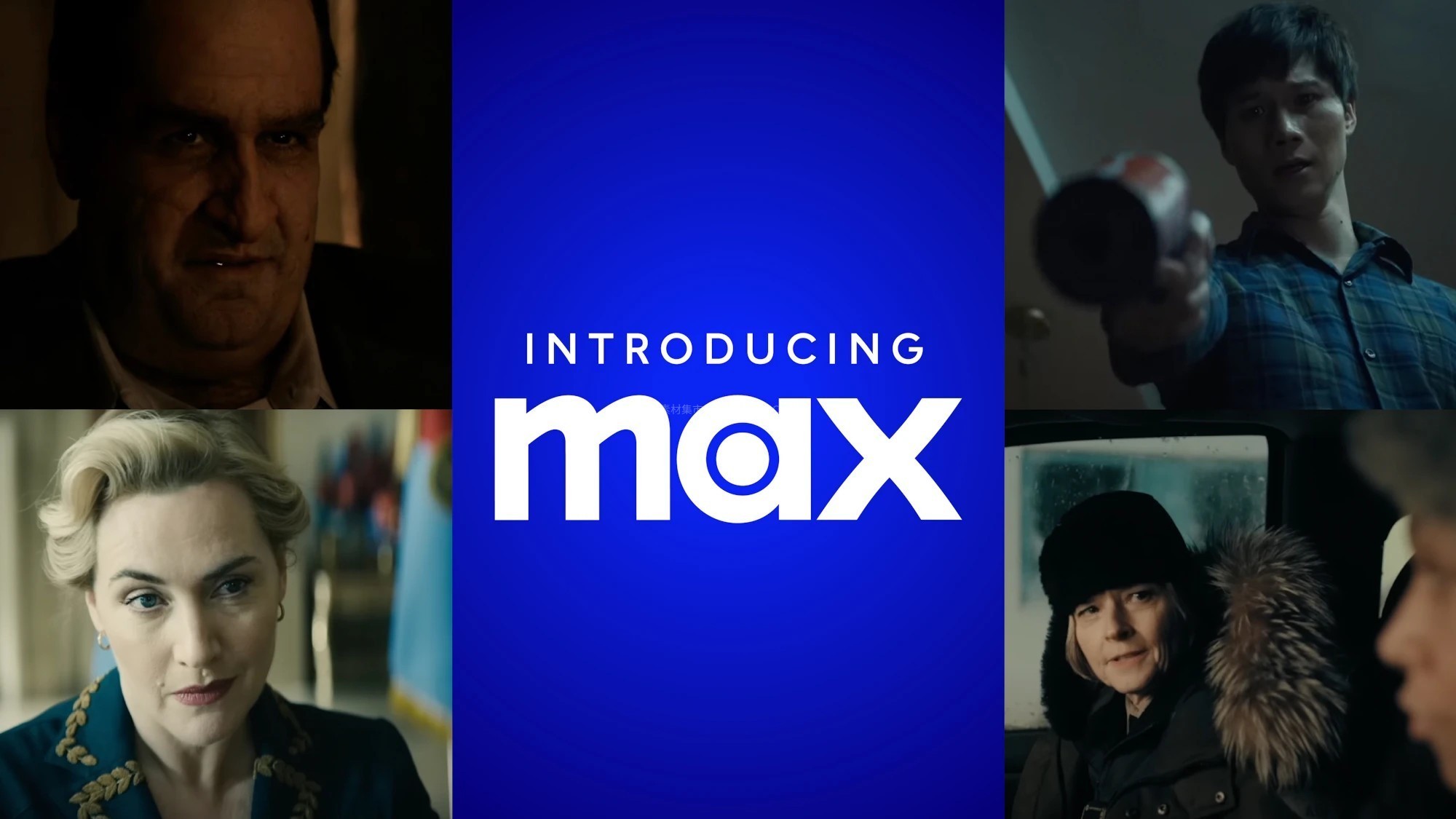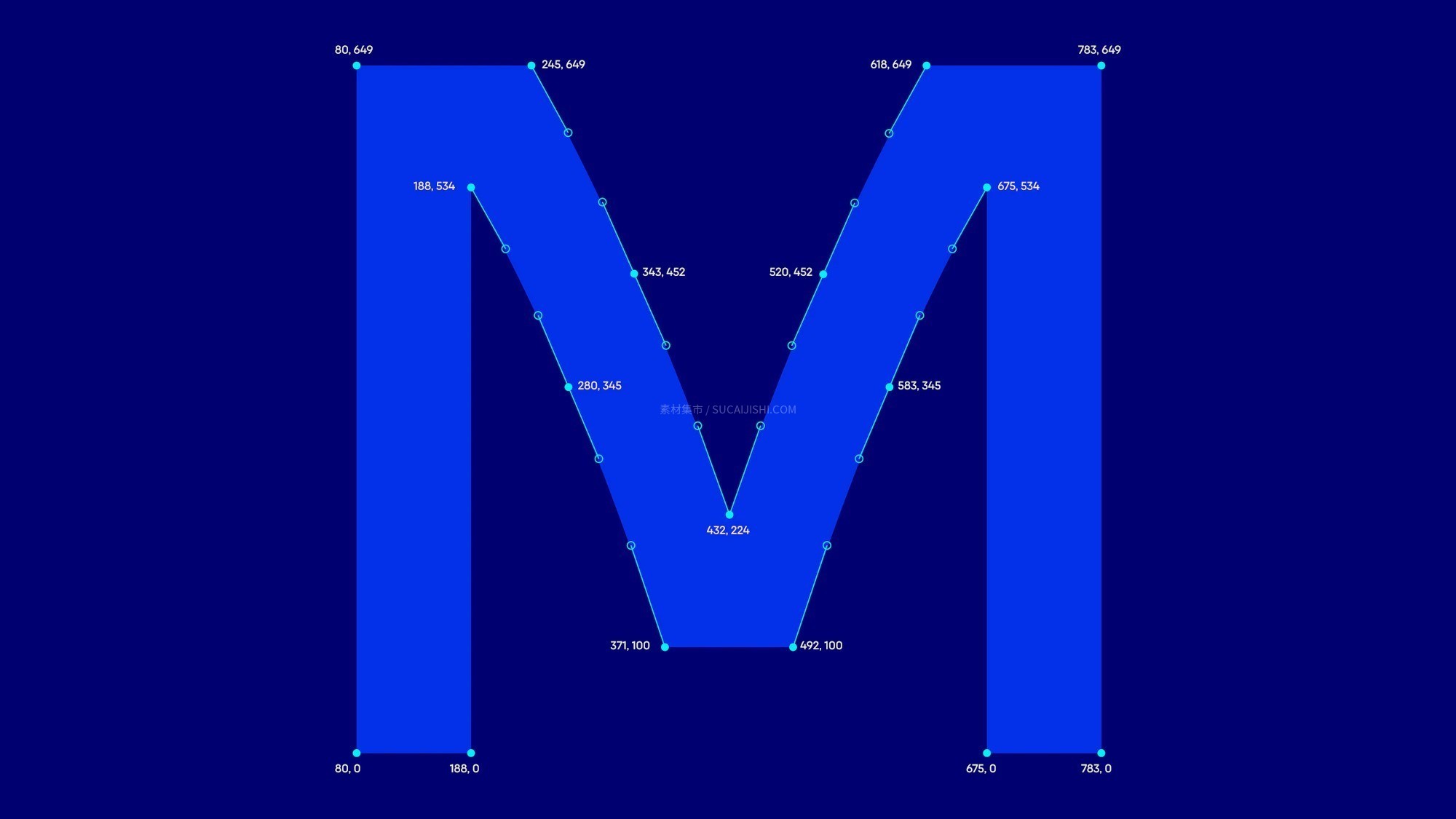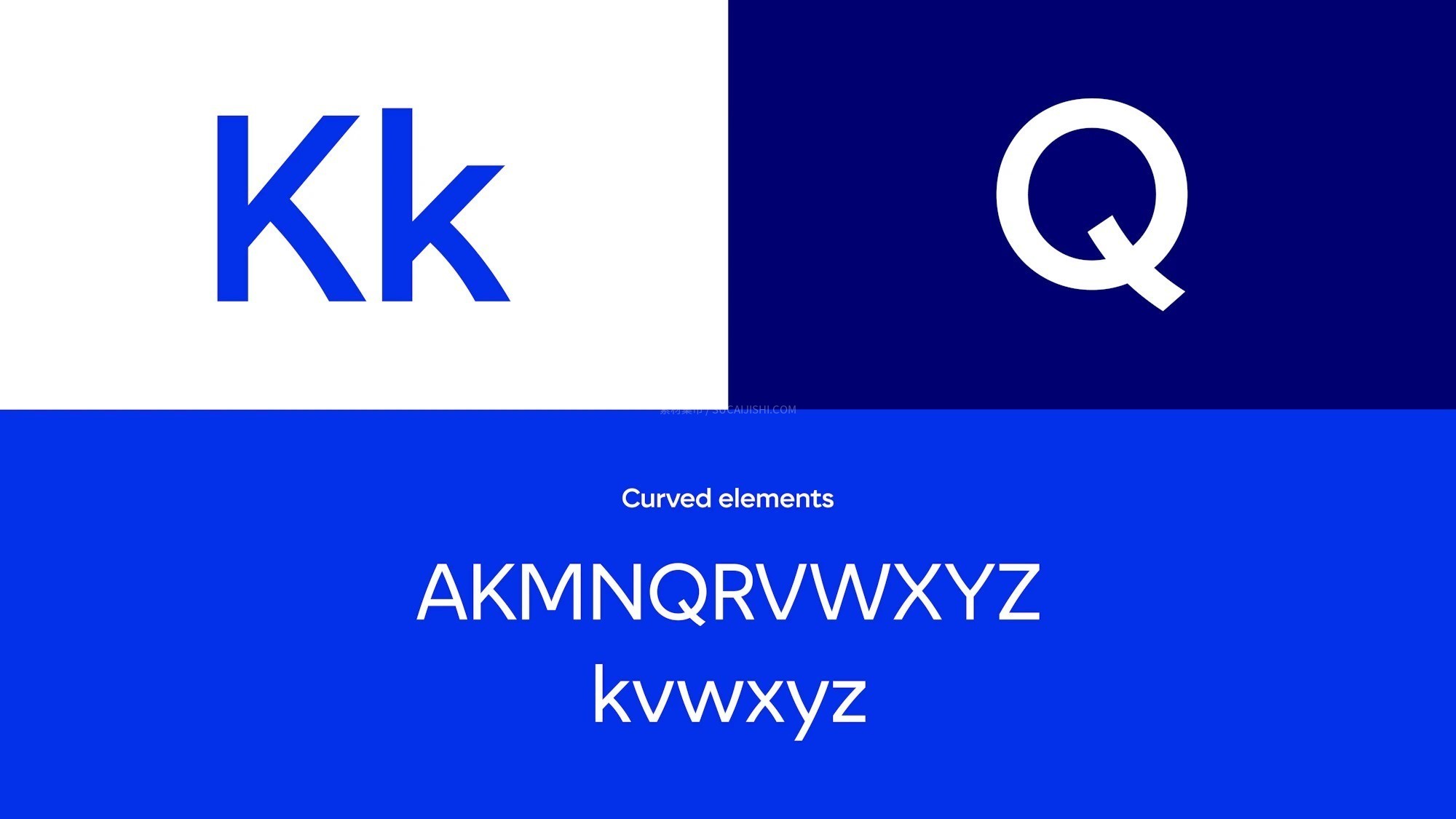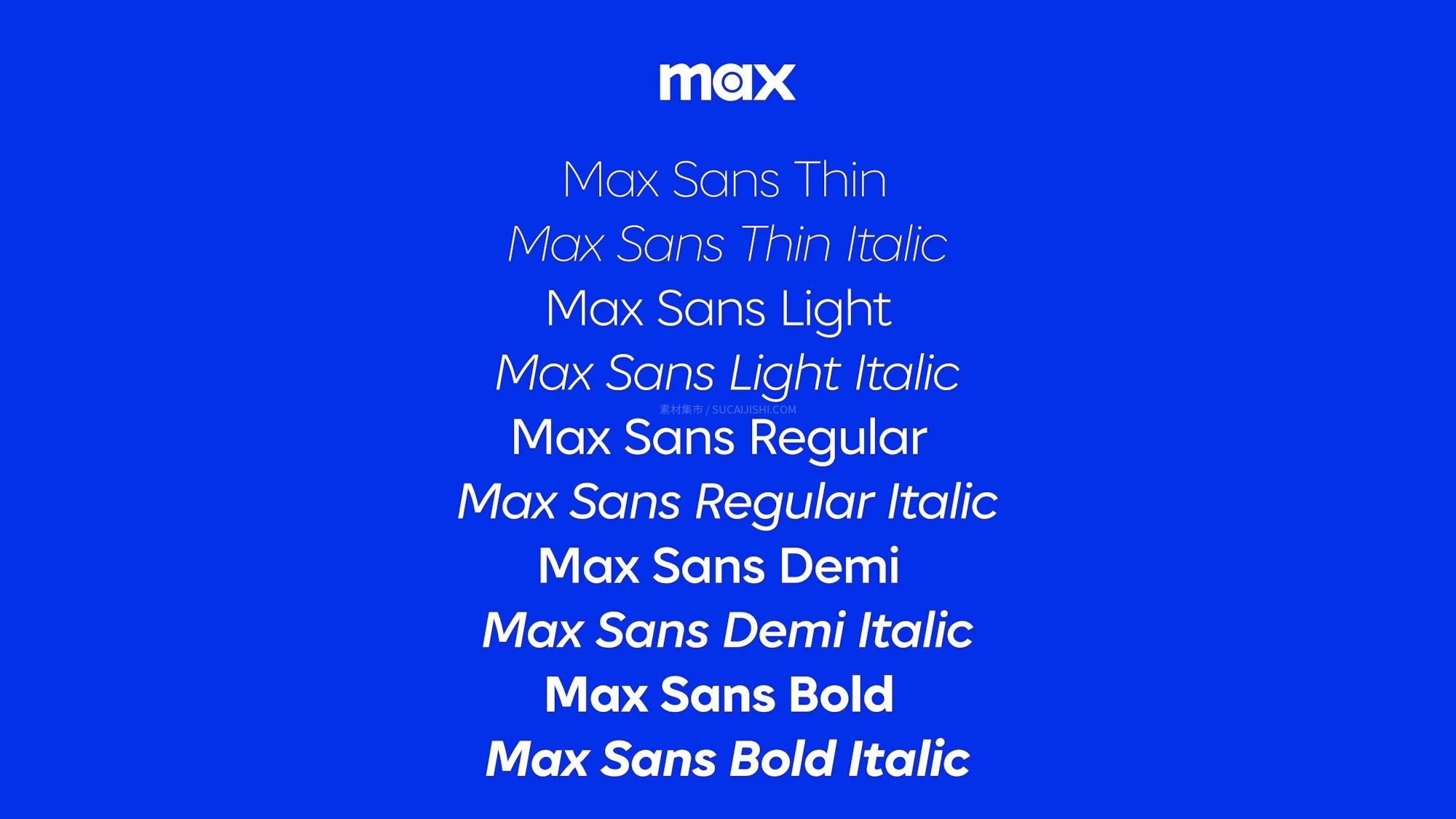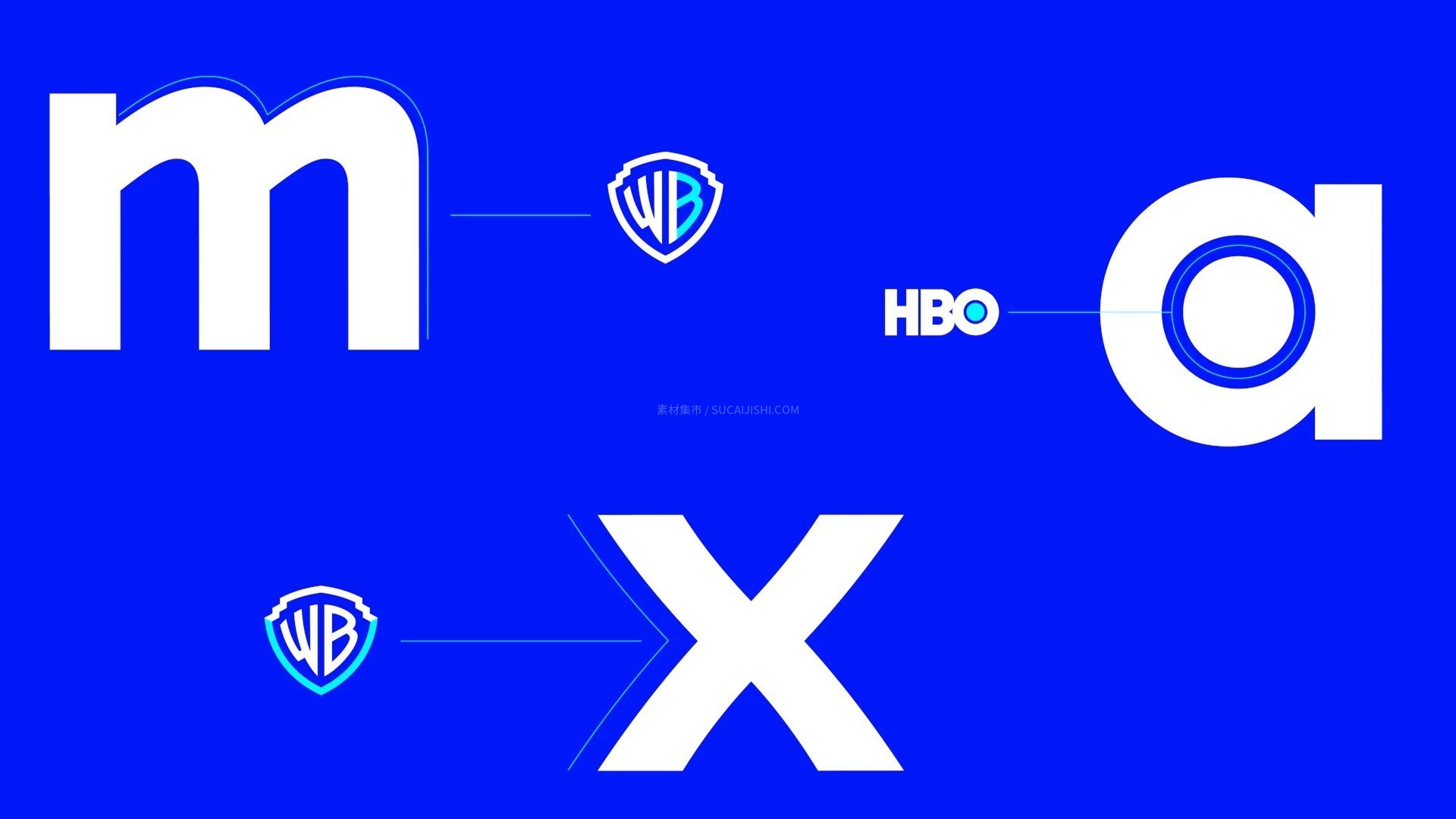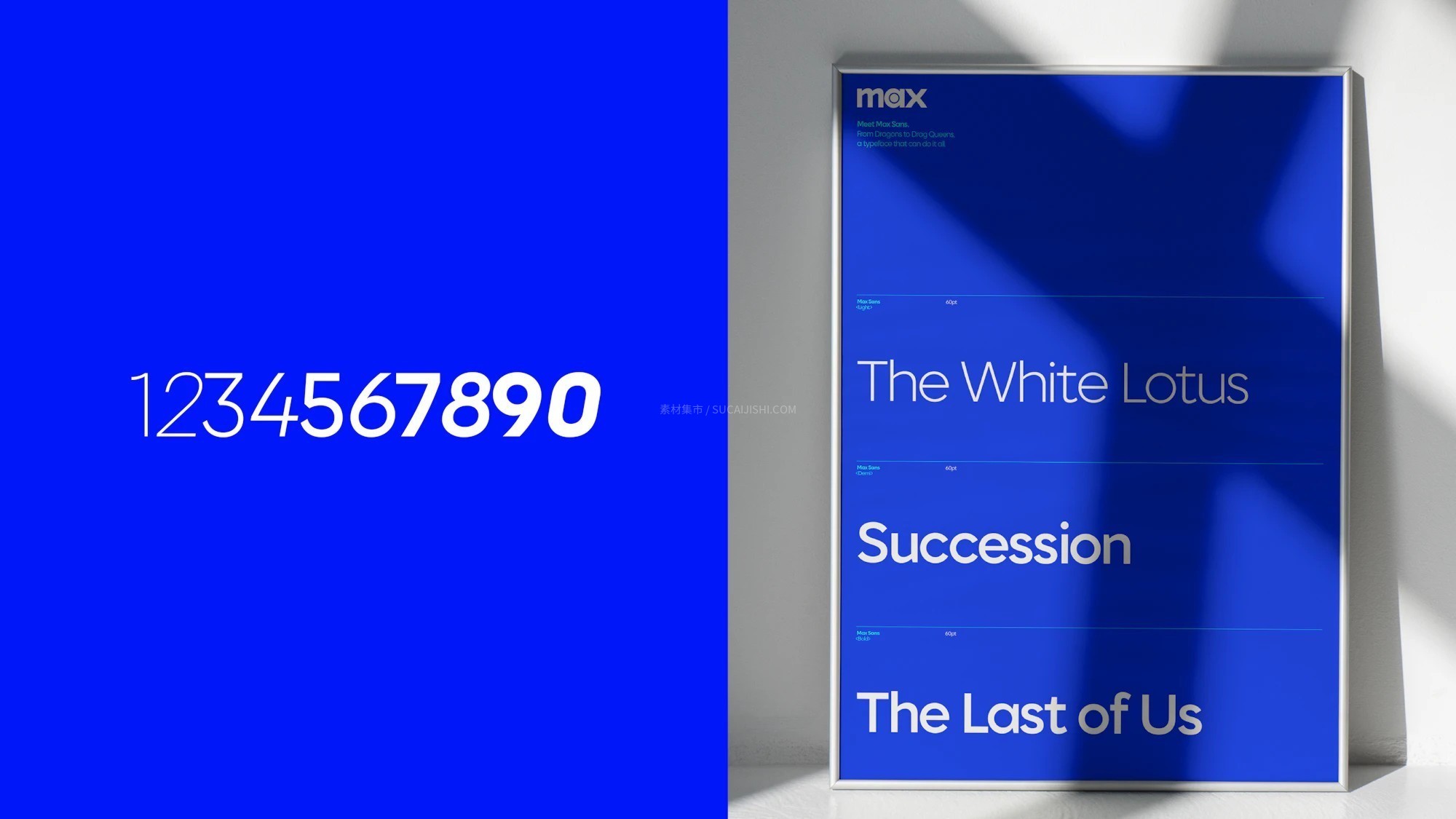
Max Sans 华纳兄弟品牌字体
大家都知道HBO Max升级成全新的“Max”了吧?这款 Max Sans 就是伦敦顶尖设计机构 DixonBaxi 联合 F37 字体公司为其量身定制的专属品牌字体哦!它在超受欢迎的 F37 Moon 基础上进行了精细改良,巧妙融入了华纳兄弟标志的经典曲线和圆形点,去掉了传统几何字体那种冷峻的棱角,视觉上超级友好圆润,同时又保留了极强的大厂辨识度和中性特质。全套包含 10 种不同样式的字重,支持扩展拉丁文、希腊文和西里尔字母等多种语言。